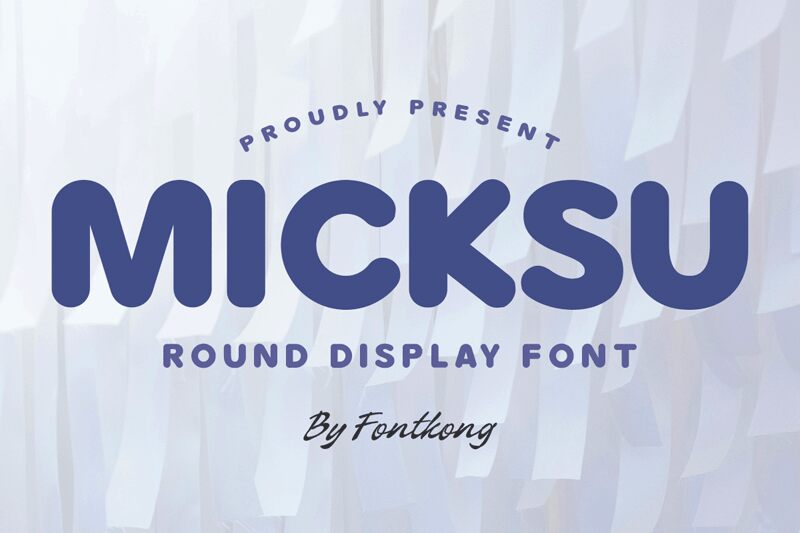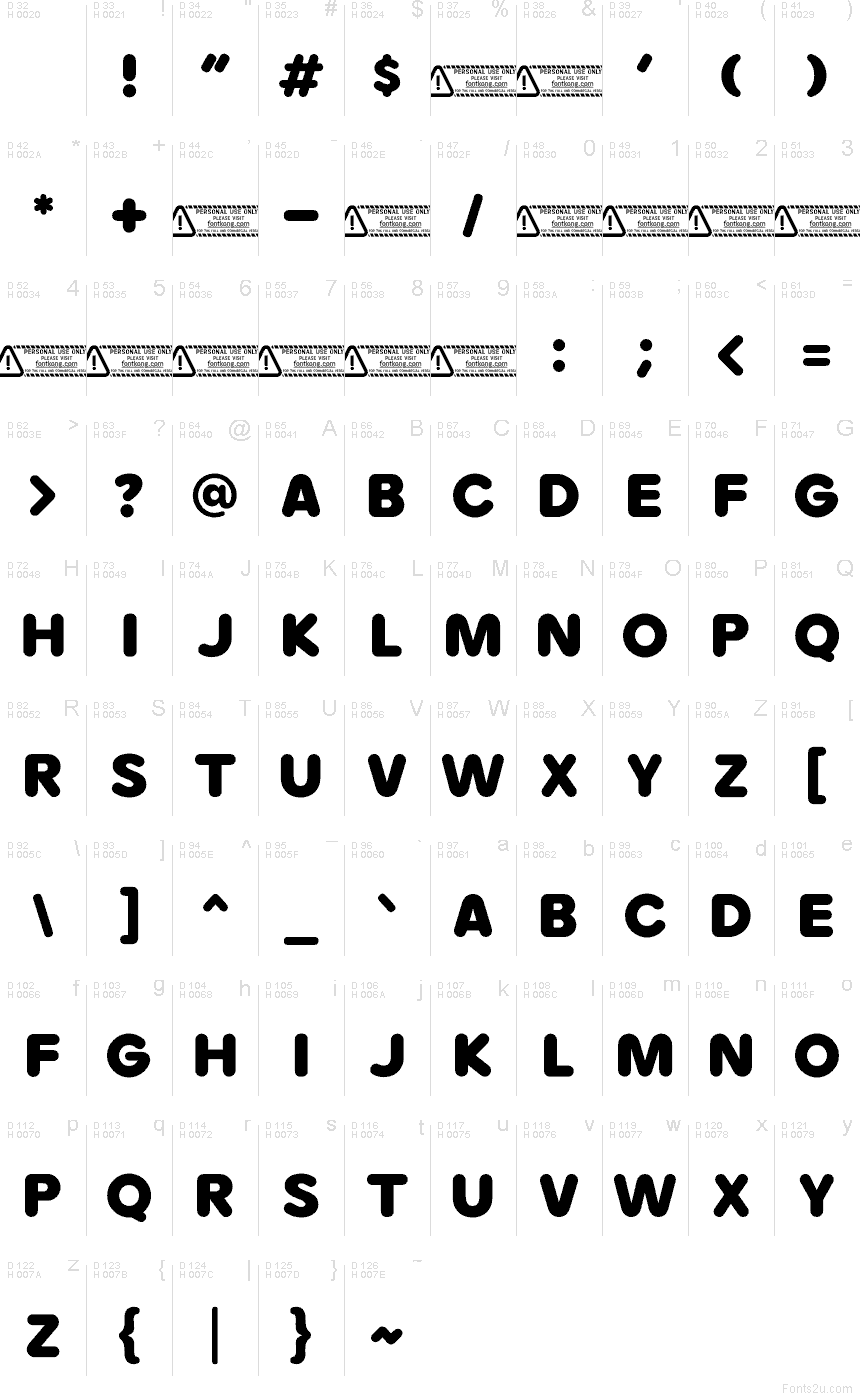
Micksuは、柔らかく膨らんだような外観と、大きく親しみやすいリズムを持つ、モダンで丸みを帯びた無料のディスプレイフォントです。文字は幅広く柔らかな印象で、太いストローク、完全に丸みを帯びた角、そしてコンパクトな文字間隔が、アルファベットに滑らかで目を引く存在感を与えています。
若者向け商品のブランディング、スナック菓子のパッケージ、アプリの起動画面、ポスターの見出し、そして遊び心のあるタイトルカードなど、短い言葉に力強く親しみやすいキャラクターが必要なデザインに最適です。無料フォントとして、Micksuはロゴやモノグラムにも非常に適しており、その太く丸みを帯びた形状のおかげで、シンプルなイニシャルでもグラフィカルで充実した見た目になります。